Шрифты научной фантастики: стиль без жанровых клише
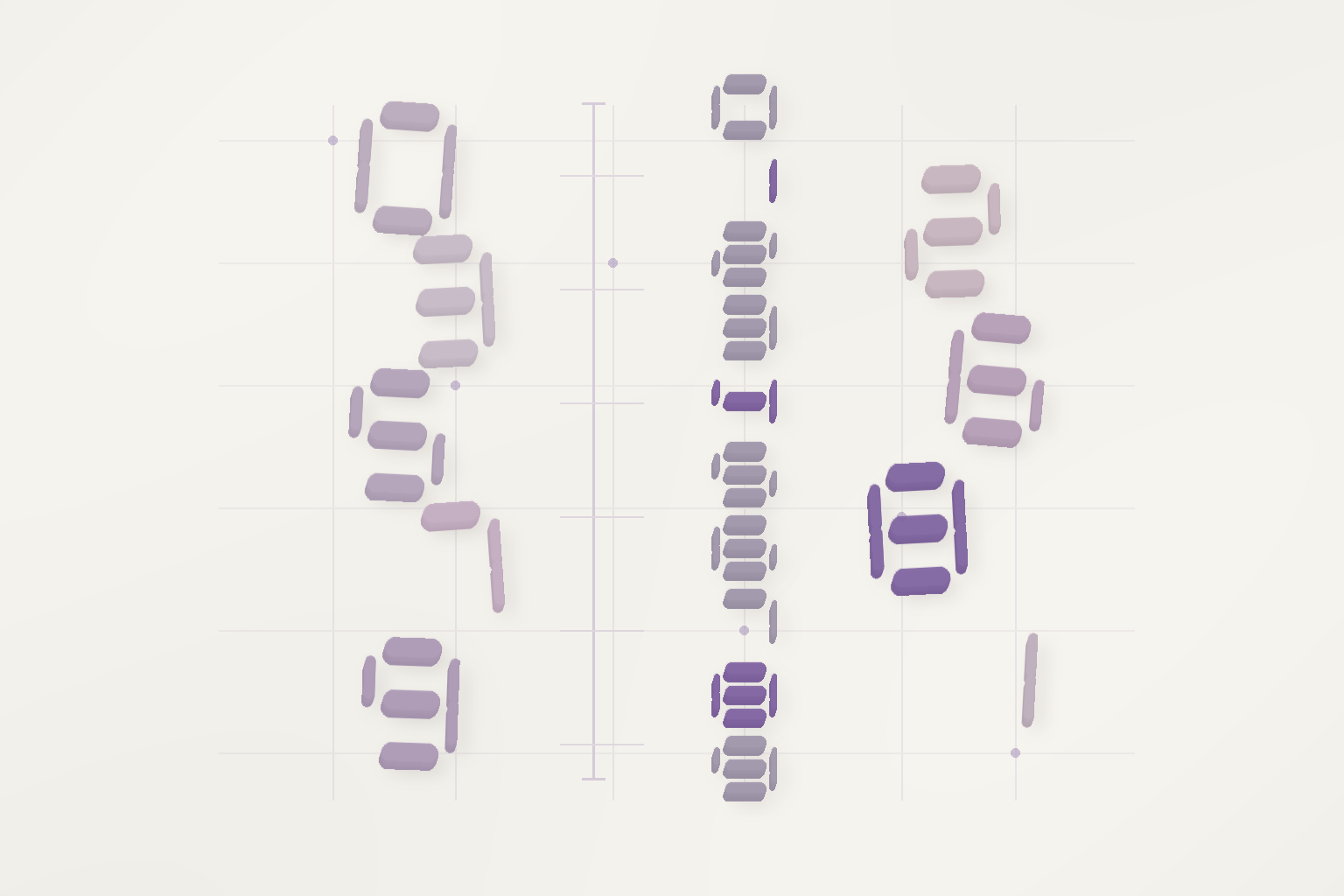
Шрифты научной фантастики передают жанровый характер не за счет очевидных символов вроде молний, голограмм и букв, похожих на схемы микросхем. Убедительный результат строится на нескольких решениях: характере контрастов, геометрии знаков, темпе набора, ширине, интервалах и качестве кириллицы. Ниже разберем, как создавать футуристическую типографику, которая намекает на будущее, но не превращается в визуальный штамп.
Что делает шрифт научно-фантастическим
Жанровый шрифт — это не обязательно декоративный шрифт с необычными буквами. Его задача — поддержать мир, в котором происходит действие: показать технологичность, иной общественный уклад, контакт с неизвестным или напряжение между человеком и машиной. Поэтому эффект будущего возникает из системы признаков. Если изменить только одну букву и добавить свечение, получится стилизация. Если изменить логику формы, ритм и применение, появляется цельный визуальный голос.
У научной фантастики нет единого шрифтового характера. Холодный технотриллер требует точной, сдержанной конструкции; космическая опера допускает масштабные пропорции и драматичный контраст; биопанк тяготеет к органическим изгибам и нестабильному ритму; ретрофутуризм использует признаки прошлых представлений о будущем. Сначала определите поджанр и эмоциональную задачу, а уже затем выбирайте форму букв.
Четыре направления жанрового характера
- Технофутуризм — рациональная геометрия, открытые формы, равномерный ритм и ощущение инженерной точности.
- Ретрофутуризм — округлые пропорции, плакатная выразительность, умеренная декоративность и отсылки к аналоговой технике.
- Биопанк — неровный контур, органические соединения, переменная ширина и ощущение живой, развивающейся формы.
- Дистопия — сжатая композиция, напряженный ритм, жесткие окончания и ограниченная цветовая поддержка.
- Космическая эпика — широкий набор, крупные пропорции, высокий масштаб заголовка и спокойная уверенная пластика.
- Постчеловеческая эстетика — необычные связи между знаками, смешение мягких и механических элементов, но без потери читаемости.
Эти направления можно смешивать, однако смесь должна быть управляемой. Например, для интерфейса вымышленной научной станции разумно взять геометрический гротеск как основу, добавить несколько нестандартных срезов и использовать моноширинный режим только для кодов и технических данных. Так возникает контраст между человеческими заголовками и машинной информацией, а не просто набор случайных эффектов.
Форма букв: как намекнуть на будущее
Самый сильный жанровый сигнал находится в конструкции знаков. Проверьте, насколько логично выглядят О, С, Е, Ж, К, М и цифры: именно они быстро формируют впечатление от шрифта. Круг можно сделать слегка сжатым, у Е — изменить длину средней перекладины, у К — сместить точку соединения, а у М — выбрать более широкую или узкую внутреннюю структуру. Важно, чтобы такие решения повторялись и образовывали систему.
Футуристический эффект часто создают не сложные детали, а непривычные пропорции. Узкий гротеск выглядит дисциплинированно и функционально, широкий — масштабно и уверенно, квадратные овалы дают индустриальное ощущение, а мягкие округлые формы делают будущее более гуманным. Перед началом работы выберите два или три главных признака. Если одновременно применить срезы, разрывы, асимметрию, контур и нестандартные соединения, текст потеряет иерархию.
Срезы, разрывы и нестандартные окончания
Диагональные срезы и разрывы штриха хорошо работают в коротких заголовках, логотипах и названиях вымышленных технологий. Они создают ощущение модульной сборки, будто символ можно заменить или перенастроить. Но прием требует дисциплины: одинаковый угол среза, сопоставимая длина и понятная причина появления. Если каждый знак разрезан по-своему, зритель воспринимает это как повреждение шрифта, а не как его язык.
Цифры и знаки интерфейса
В научно-фантастическом дизайне цифры иногда важнее букв: они появляются на панелях, шкалах, координатах, датах и маркировке оборудования. Сначала разработайте 0, 1, 2, 4, 7 и 8, затем проверьте, различаются ли 0 и О, 1 и I, 5 и S. Для интерфейса полезны табличные цифры одинаковой ширины, а для плаката — пропорциональные, более выразительные знаки.
Ритм, ширина и интервалы важнее декора
Даже необычная форма не создаст убедительный образ, если набор разваливается. Ритм определяется чередованием черного и светлого, шириной знаков, размером апертур и расстояниями между буквами. Для технологичного шрифта нужен контролируемый ритм без случайных провалов. Для биопанка допустима неровность, но она также должна повторяться по всему алфавиту. Жанровый характер считывается в строке целиком, а не в одной эффектной букве.
Трекинг способен изменить настроение сильнее, чем декоративный элемент. Увеличенные интервалы создают ощущение стерильности, масштаба и дистанции; плотный набор усиливает тревогу, давление и дефицит пространства. Не задавайте универсальный интервал для всех применений. Заголовок на постере, подпись к объекту и длинный абзац требуют разного темпа. Если шрифт должен работать в интерфейсе, проверяйте его прежде всего на небольшом кегле.
Вывод: фантастика начинается с логики формы